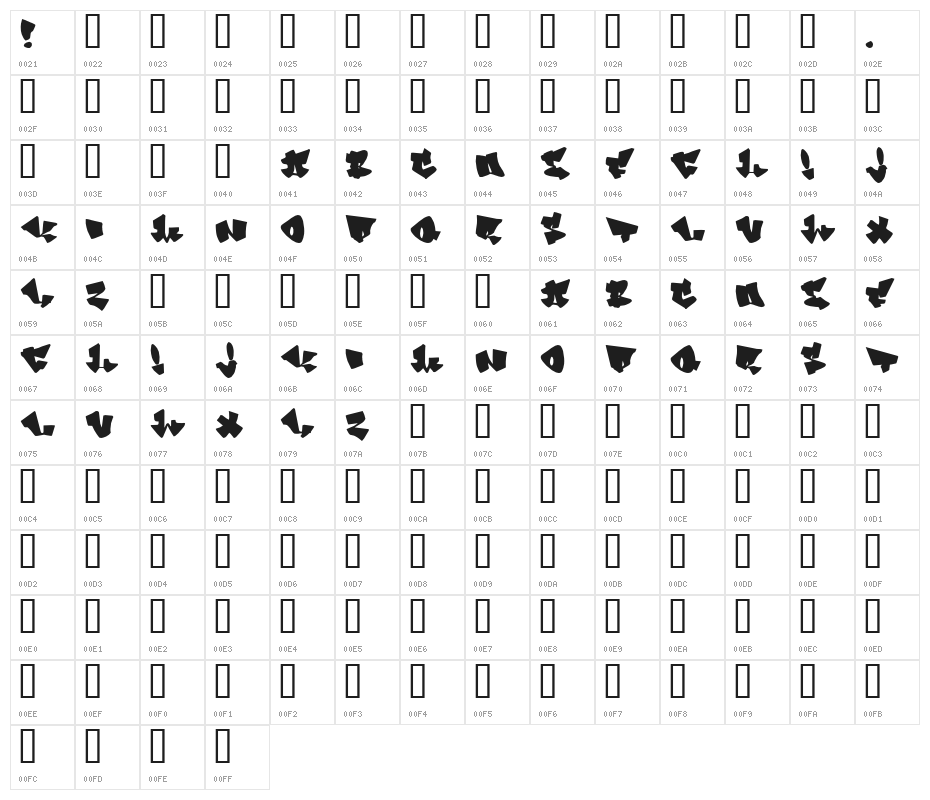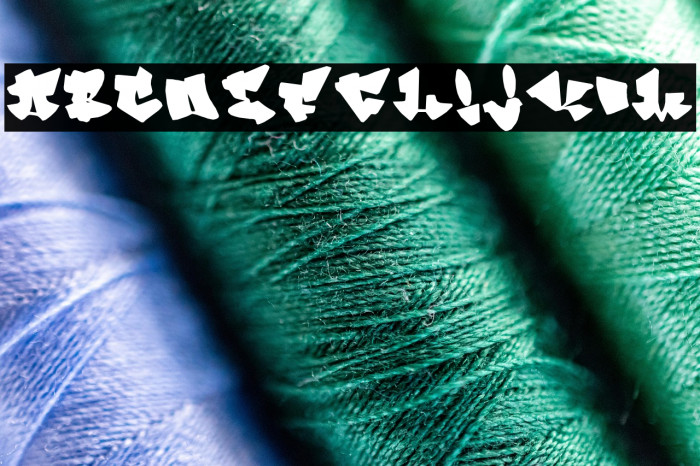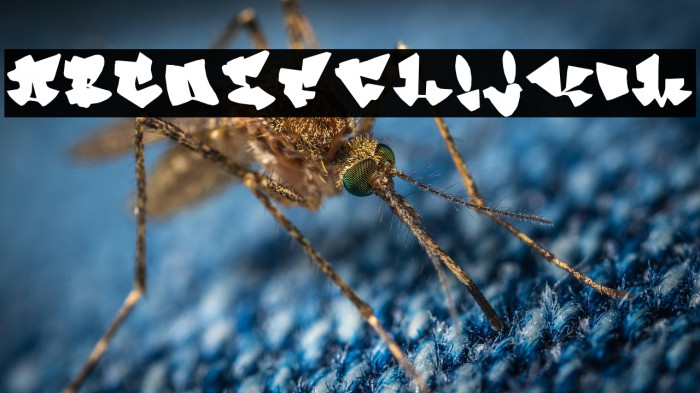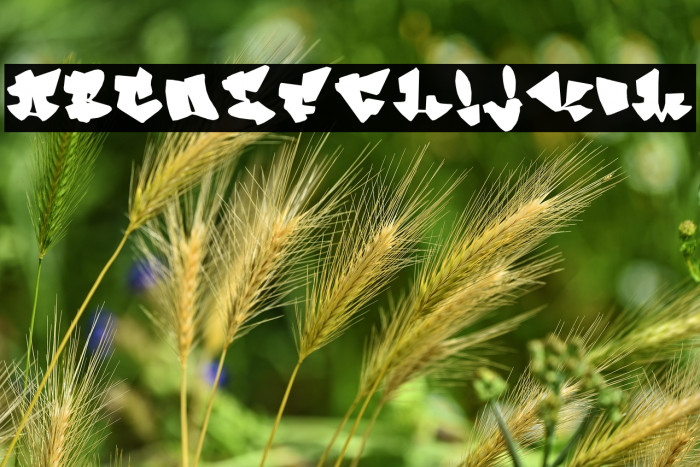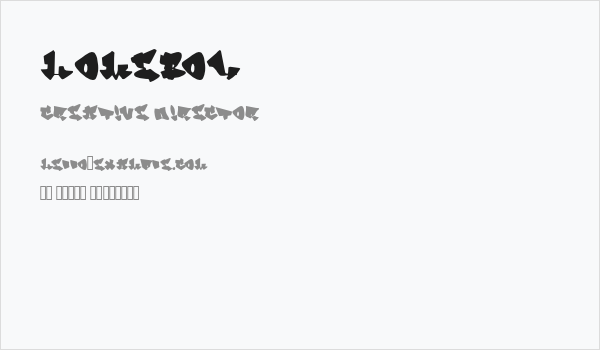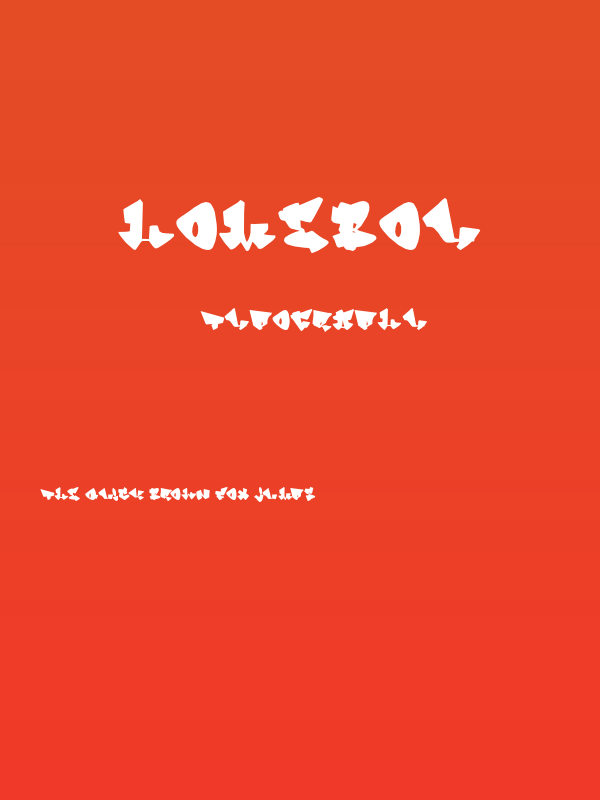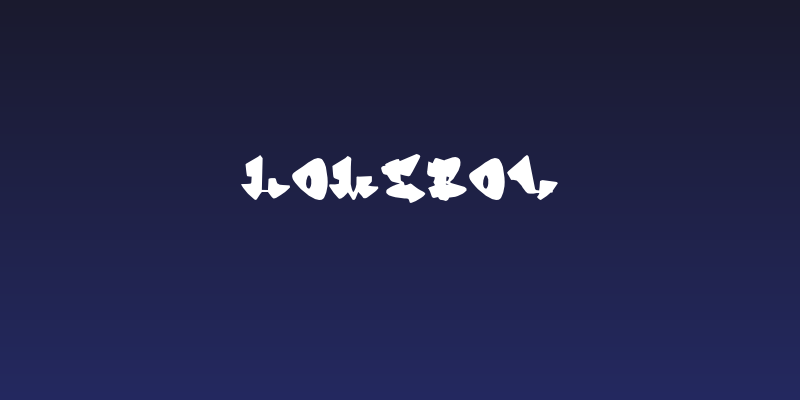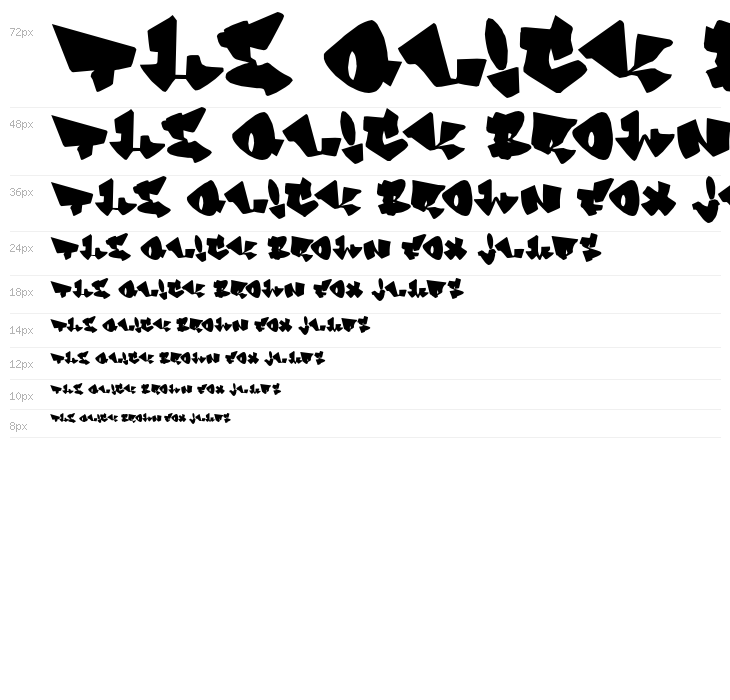
Homeboy Font
✎ Graffiti
| Gesamtstil | Urban, Graffiti, Bold |
| Vorgeschlagene Projekte | Perfect for street art projects, urban-themed posters, music album covers, and edgy branding. |